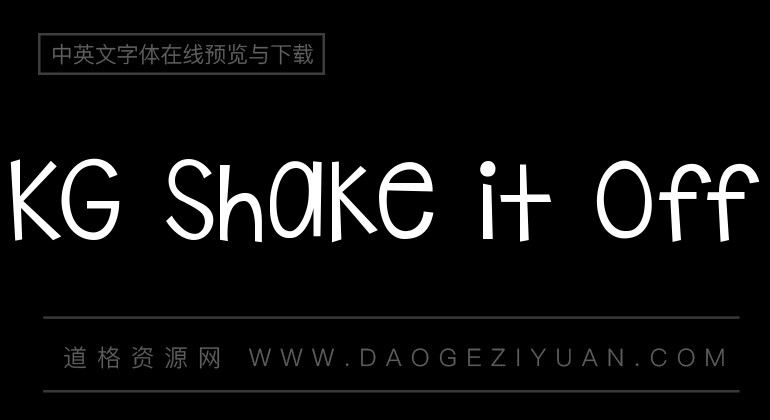
KG Shake it Off
? KG Shake it Off 字体是一款由Kevin Guttman设计的手写体字体。它拥有轻松、活泼的外观,可以帮助您的文字脱颖而出。它的字形字体具有粗细变化,使您的文字看起来更有活力,更有表达力。它的字体也有精致的细节,使您的文字更加引人注目,更有质感。它具有优雅的外观,可以帮助您轻松实现自己的设计理念。
KG Shake it Off是一款非常不错的手写艺术字体,具有很好的视觉感,适合于文化类的宣传设计、商业类品牌的广告和产品包装设计以及个性化文字排版等较多场景。